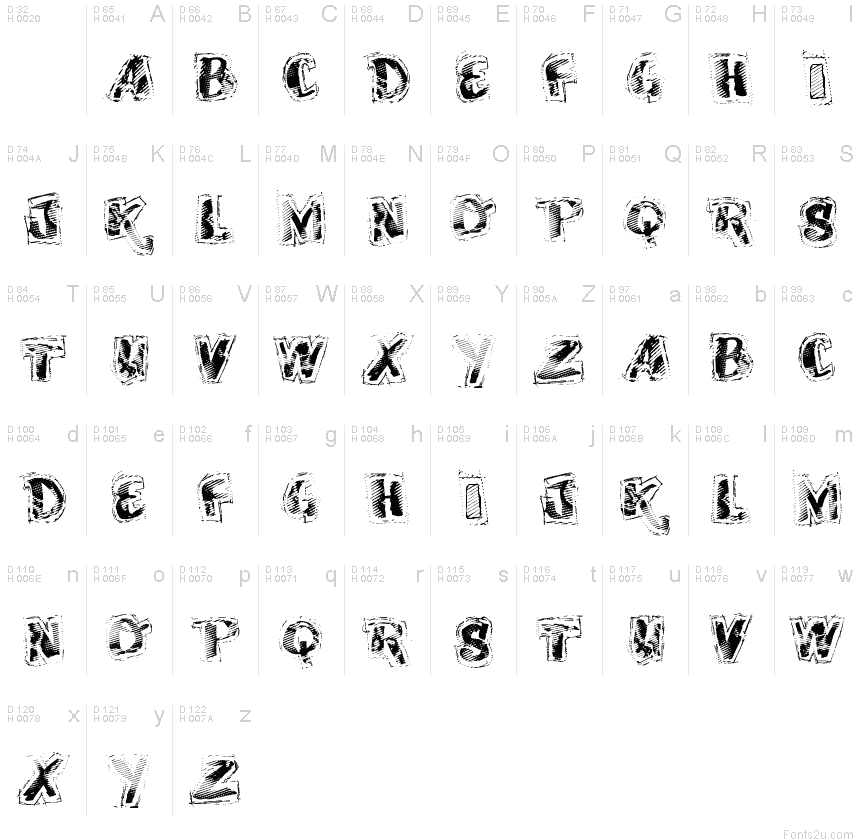
VTKS Scrubbed autorstwa Douglasa Vitkauskasa to darmowy krój pisma typu grunge display o surowym, wytartym wyglądzie, jakby wyjęty prosto z kserowanych ulotek czy miejskich grafik rysowanych markerem. Litery wyglądają na zdrapane, przelane tuszem i lekko przesunięte, z poszarpanymi krawędziami i szkicowymi cieniami, które sprawiają, że cały projekt jest niespokojny, a nie uporządkowany.
Ten darmowy font świetnie pasuje do plakatów, okładek zinów, grafik albumowych, napisów tytułowych, brandingu skate lub punk oraz krótkich nagłówków, gdzie ta zniszczona tekstura może grać pierwsze skrzypce. Sprawdzi się też w szkicach logotypów i wyrazistych nagłówkach, ponieważ nierówne kontury i przetarte wypełnienie nadają nawet kilku słowom natychmiastowego, ręcznego charakteru.